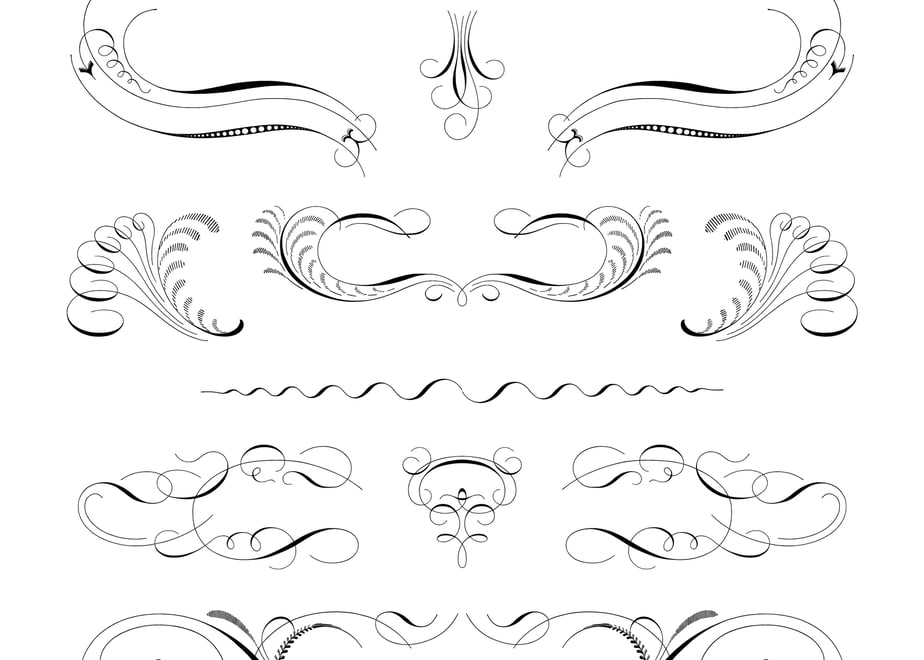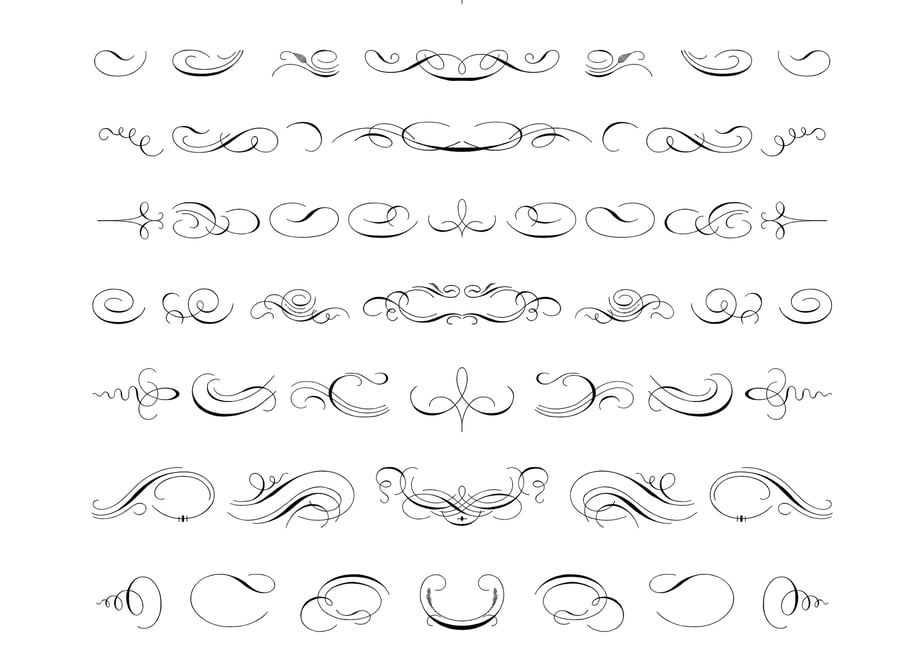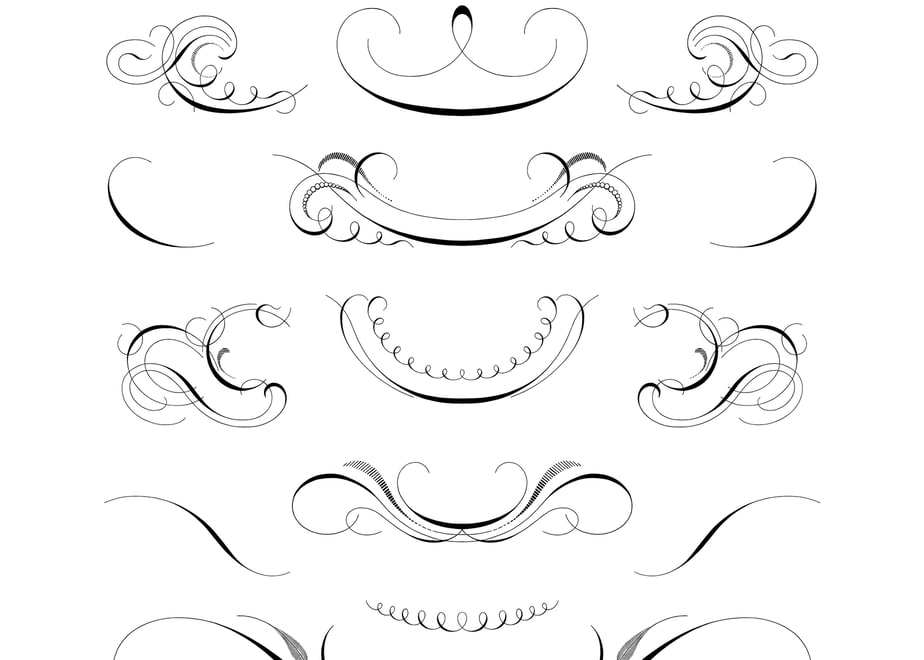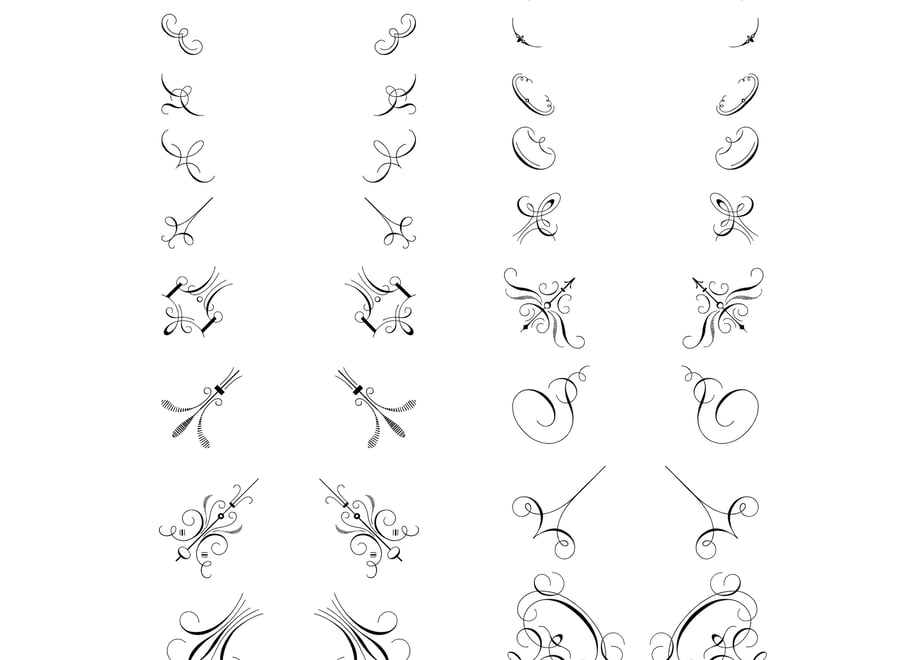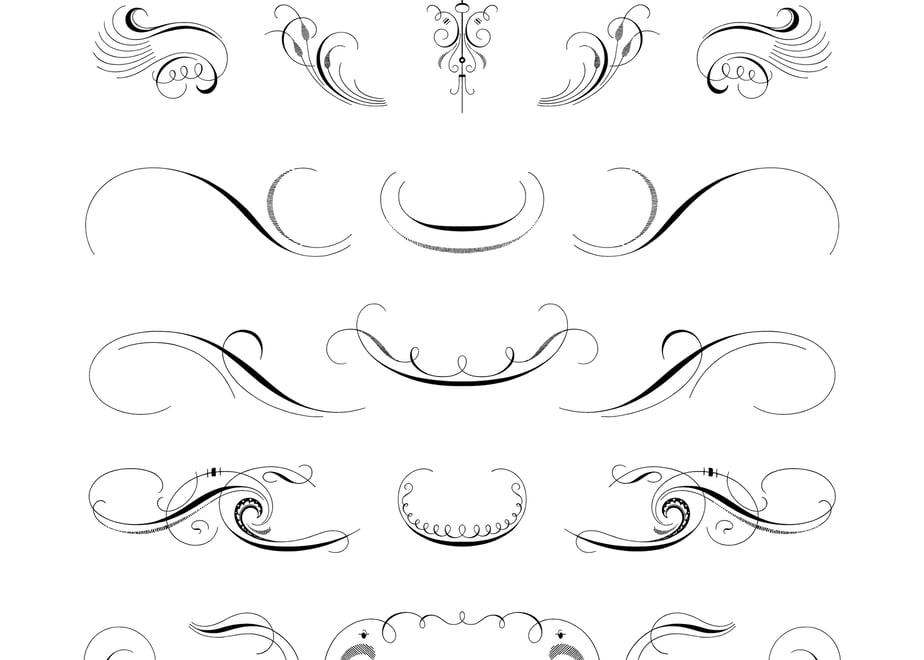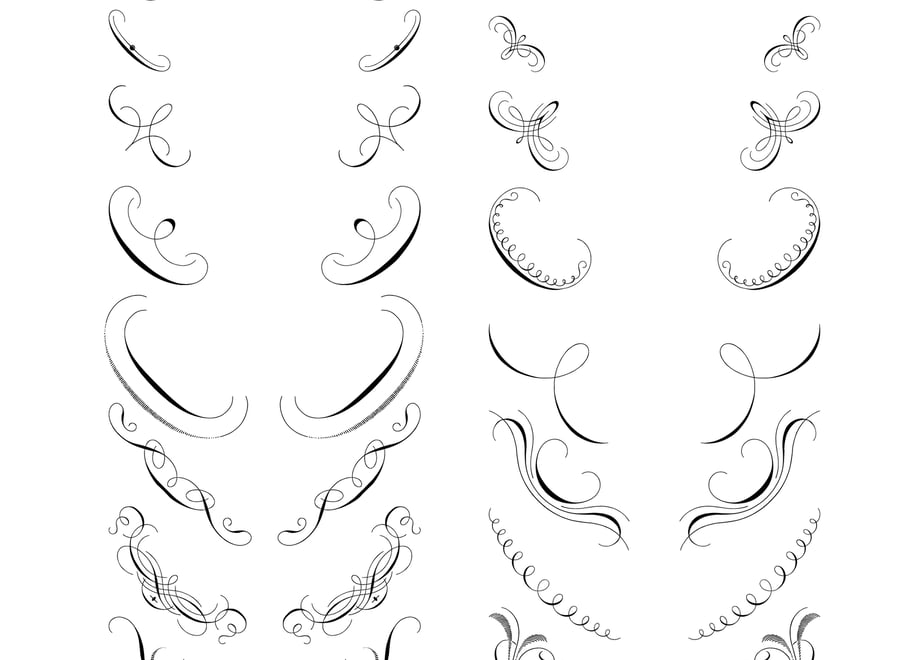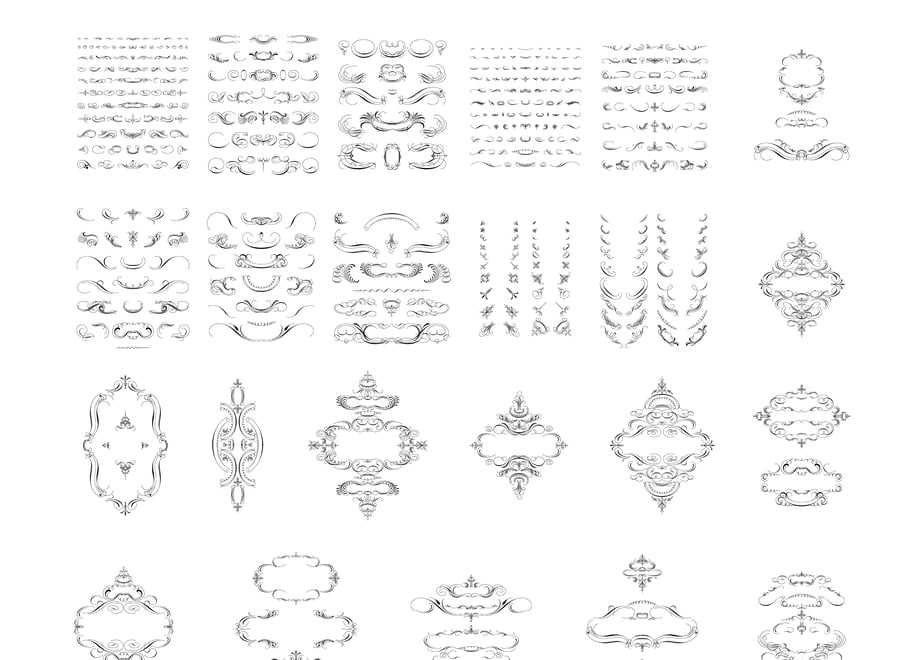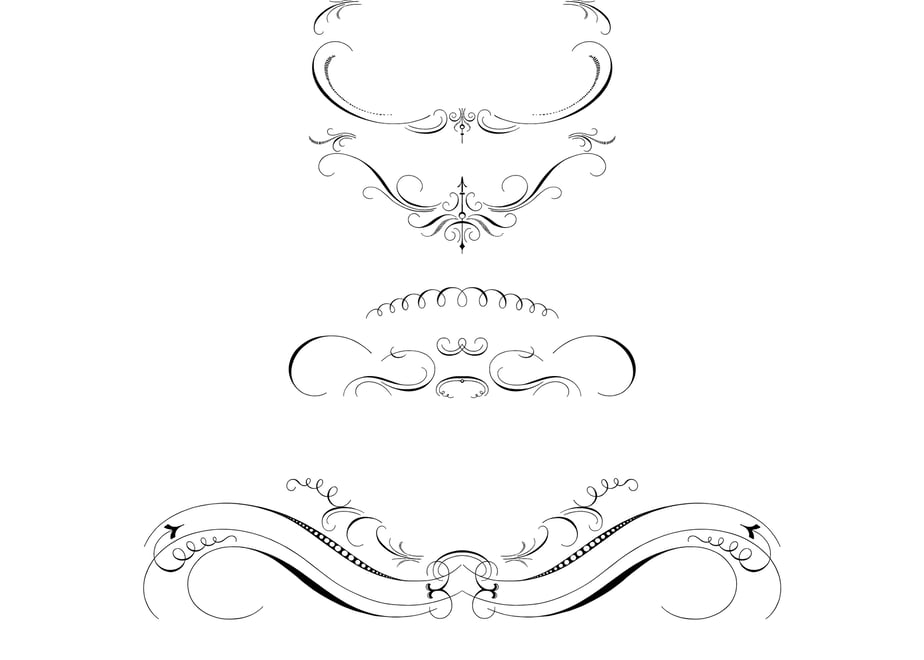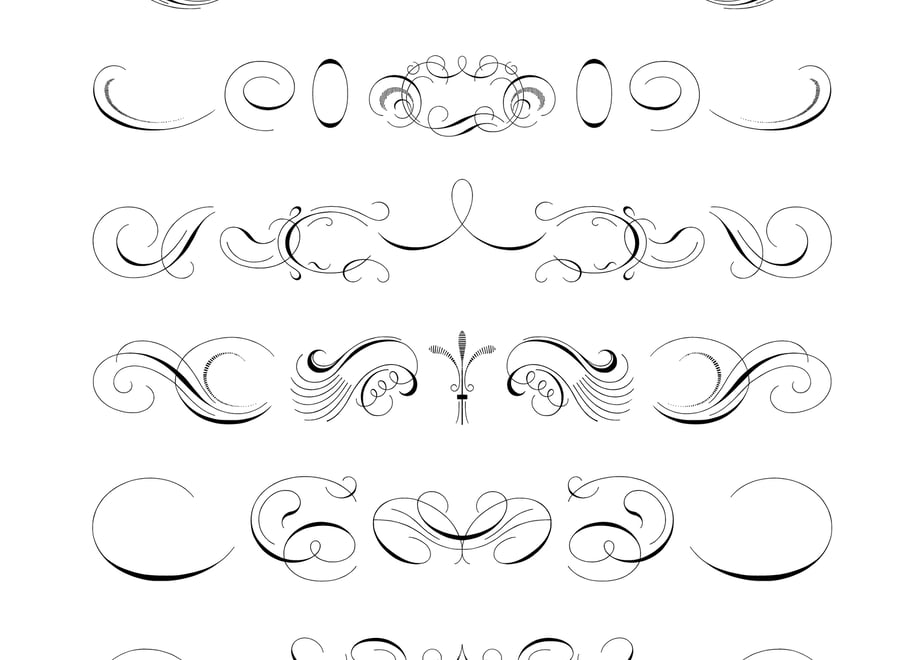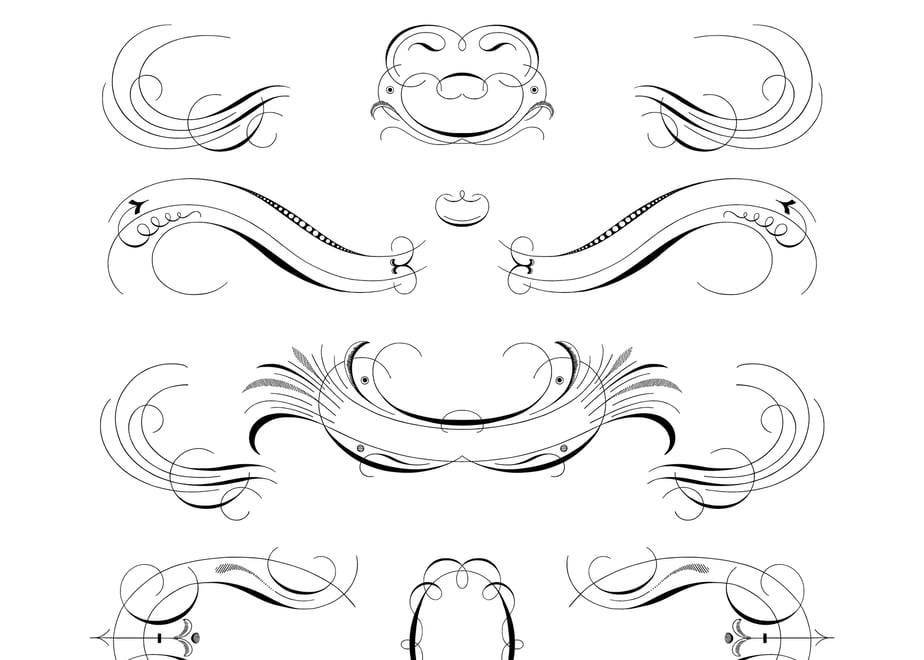
装飾活字:Gravure et Fonderie C. Derriey. Specimen-album. [TRAITS DE PLUME]
1862年に Gravure et Fonderie de C. Derriey によって発行された「Gravure et Fonderie C. Derriey. Specimen-album.」に収録された [TRAITS DE PLUME] の装飾をもとに、現代のデザイン環境で利用できるよう再構築したデータパッケージです。
資料に収録された装飾の形状や構成を可能な限り保持しながらデジタル化を行い、グラフィックデザイン、エディトリアルデザイン、ロゴ制作、パッケージデザインなど幅広い用途でご利用いただけます。
本プロジェクトは、フランスの美術大学図書館でデジタルアーカイブに携わる方とのご縁から始まりました。高解像度でスキャンされた原典資料をご提供いただき、そのデータをもとにAdobe Illustratorで一点ずつ丁寧にアウトライン化を行っています。
本商品では、「Gravure et Fonderie C. Derriey. Specimen-album.」に収録された [TRAITS DE PLUME] の装飾を採録し、現代のデザイン制作で活用できる形に再構築しています。
TRAITS DE PLUME は、ペンによる描線表現を用いて構成された装飾図案群です。
花形装飾活字とは異なる軽やかな線の表現が特徴で、見出し装飾やフレーム、区切り罫、誌面装飾など幅広い用途に活用できます。
19世紀フランスにおける印刷装飾文化の一端を伝える貴重な資料を、現代の制作環境で利用できるデータとして再構築しました。